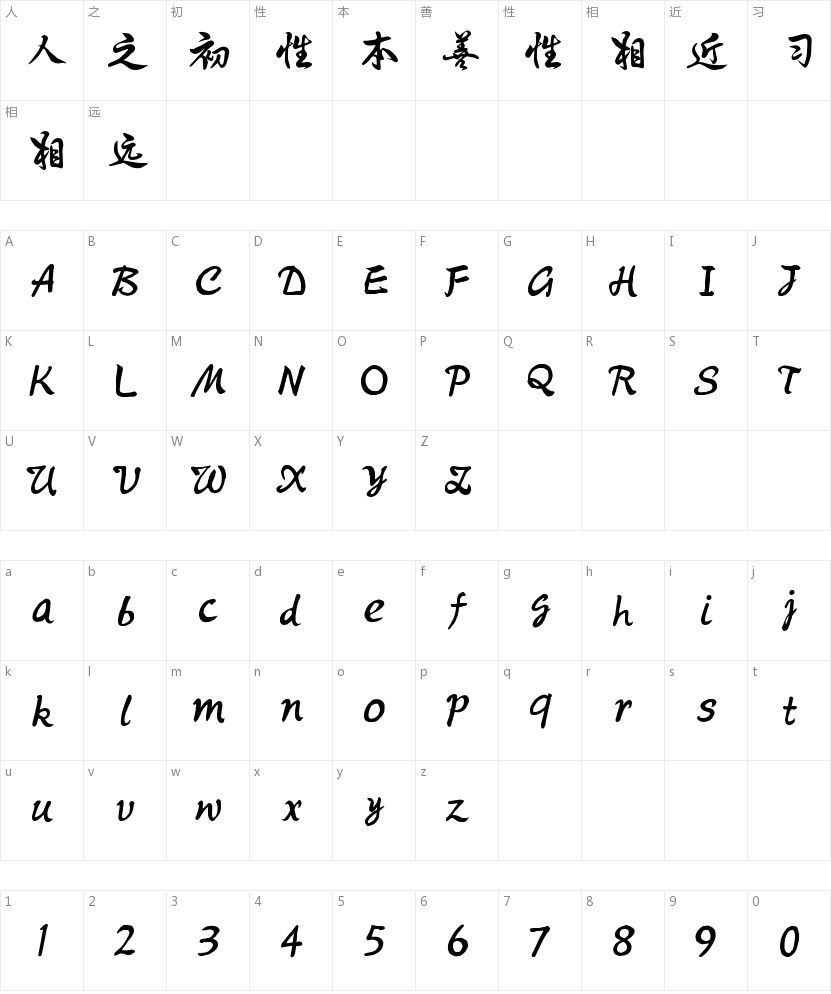
腾祥伯当行书简体
腾祥伯当行书简体字体是由腾祥伯当行书团队设计的一款简体中文字体,它融合了汉字的传统笔画风格,以及新兴的现代笔画风格,让字体看起来更加立体、精致,更具有传统文化特色。腾祥伯当行书简体字体丰富的笔划和细腻的曲线,使字体更加灵动,具有浓郁的文化气息,可以应用于各种类型的文字,也可以用于印刷、多媒体和网络等多种场景。
腾祥伯当行书简体是一款非常不错的手写艺术字体,具有很好的视觉感,适合于文化类的宣传设计、商业类品牌的广告和产品包装设计以及个性化文字排版等较多场景。